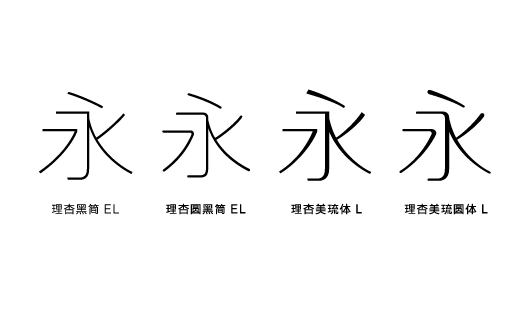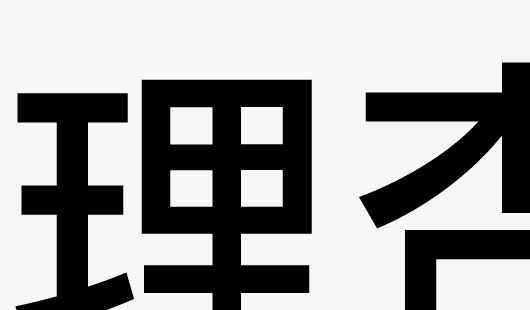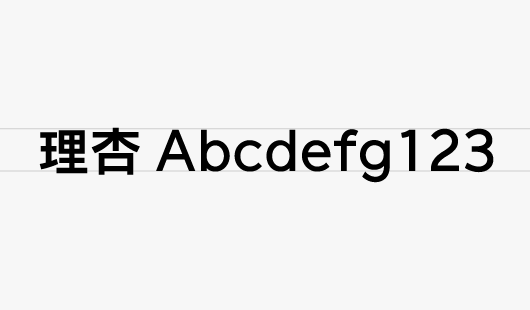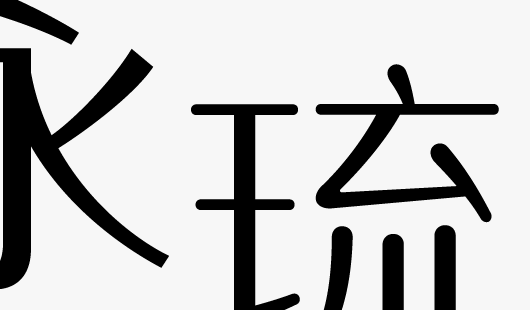
「向谁传达?」「传达什么?」「要留下什么印象?」
传达思绪具象化的是文字。
能够将文字的作用发挥至极致的道具,则是字体。
理杏字体赋予文字不同的表现形式与个性,通过想象作者在书写文字时想要传达的感情信息,
让字体成为载体,在表达内涵的同时,也充满美感与魅力。
理杏字体是由中国与日本字体设计师共同开发的中文简体字体。中日字体设计师对中文简体字特有字形不断进行研究探讨,并对细节的精雕细琢,从而诞生的高品质中文简体字体。积极追求“简洁”“细致”“品质”的理杏字体,直到完成前不久,设计师们还反复地在显示器上、打印稿上校对、检验,无数次的修改,对一点一笔一划都尽可能讲究完美。以严谨而细致的工作态度而诞生的理杏字体,相信会活跃在各种视觉设计中,毫无疑问会为客户的品牌建设锦上添花。
理杏字体具有优美易读,简洁中和的理杏黑简系列,以柔和精致的字形为特点的理杏美琉简系列与生动流畅的理杏美琉圆简系列等。
理杏字体的细致与品位,只为品牌形象的提升而存在。
理杏字体是融合了中日平面设计师感性与字体设计师匠心的、与众不同的、从全新的角度开发的中日融合型的新系统字体品牌。在字体设计上,不仅非常重视“易读性”,还兼顾平面设计时涉及到的“实用性”“易选性”具备的字形设计。比如,作为正文字体开发的“理杏黑简系列”“理杏圆黑简系列”等,同时也开发了极细字号,使其兼具纤细与实用两种特性。
作为理杏字体所有系列中相对时尚的黑体字体“理杏黑简系列”,其笔画设计以“直线”为主题,形成文字横线的笔画都以直线起笔,曲线部分从始至终,都尽量保持等宽,不赋予其过多抑扬顿挫而开发的字体。作为理杏黑简系列核心的“EL”,在用于大型平面设计的主文案等时,文字的每一笔每一画都由均一的浓度构成。
为了提升理杏字体作为中文活字的可读性,在设计每一个文字时,最大限度地利用空间,放大文字。此外,在文字排版时经常会碰到中文与非汉字文字组合的情况,为了保持整体的美观与平衡,调整非汉字文字的大小及粗细,使文字间的组合保持自然与整体感。此外,理杏字体导入了人性化的“UD Fonts(Universal Design Fonts)”概念,通过对每个字的细节调整,提升英数字辨识度,使文章更易于阅读。
理杏字体的新成员“理杏美琉简系列”,重新构筑以往字体设计的理念,例如,就像平面设计师为全新品牌开发标志标准字时一样,需要非常彻底地将新的规则运用在字形设计上,于是史无前例的全新个性得以孕育而生。美琉体最大的特征在于彻底颠覆了“点”的入笔与收笔的顺序。与宋体等衬线字体所有的抑扬感不同,美琉体就像用签字笔优雅地书写一般,既有黑体端庄的一面,又有宋体优雅的一面,充满个性却又不失温柔的字体。
由于理杏字体是日本开发的中文字体,因此全字体中都完整收录了与中文字体设计感完全一致的平假名与片假名设计,如有假名与文字混杂的文档,相信一定能发挥其效果。
现如今,中文数字字体的世界被众多规则所约束,也存在着无法被字体使用者正确理解,甚至完全不被了解的规则。理杏字体通过设定易于使用者导入和使用的规则,来打破这种状态,开发出更多拥有至今为止闻所未闻的全新设计性的字体。新颖的、优雅的,今后也将不断发布各种各样、个性迥异的设计字体,欢迎使用。